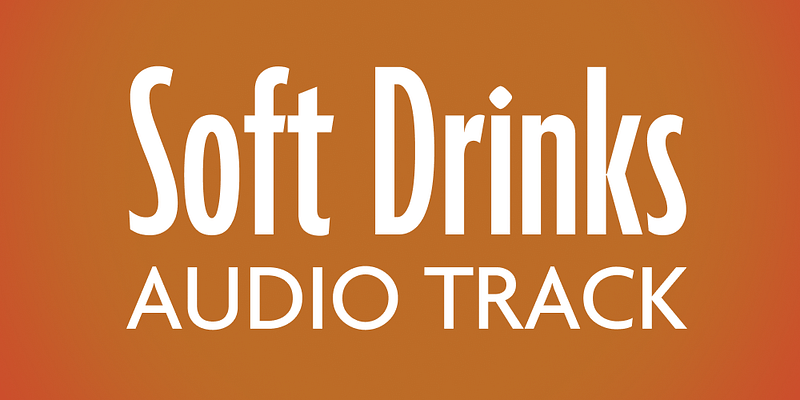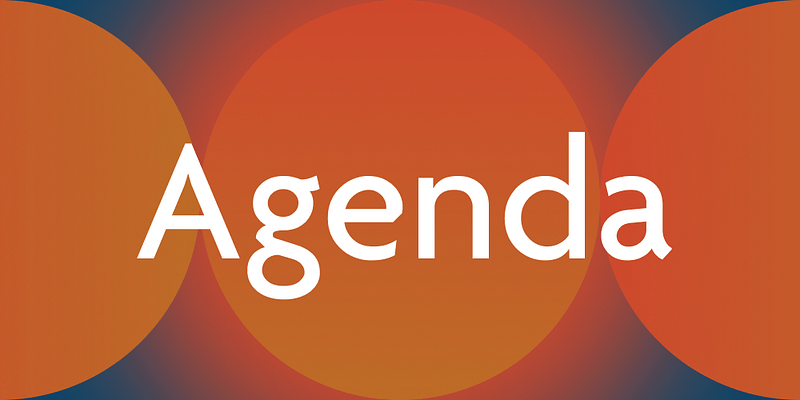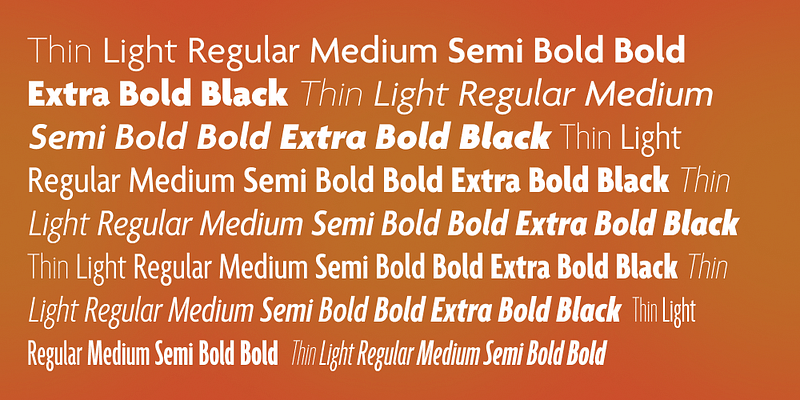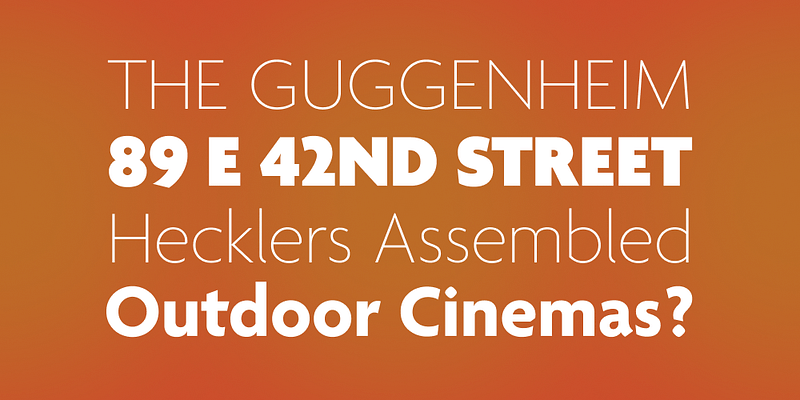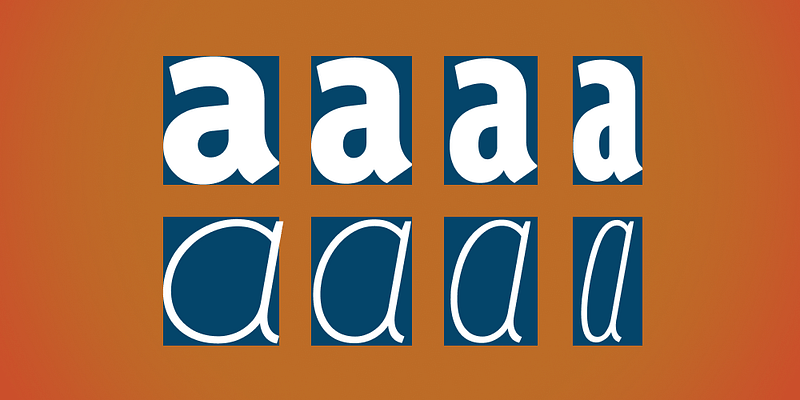
Agenda는 90년대의 상징적인 서체 중 하나입니다. 그 광범위한 패밀리는 완전히 정비되었고 Agenda One으로 재출시되었습니다. 깔끔하고 매끈한 휴머니스트 산세리프체는 Thin에서 Black까지의 Regular, Condensed, Extra Condensed 및 Compressed 폭과 무게의 타이포그래피 올인원 솔루션입니다.
Agenda One에는 현재 Agenda 소매에 설정된 문서가 Agenda One으로 변경될 때 문자 폭이 약간 다르게 리플로우될 가능성이 충분히 있습니다. 헤드라인 및 보다 큰 유형의 리플로우는 더 넓은 스타일에서 더 적게 발생하고 더 좁은 스타일에서는 가능성이 더 높지만 텍스트 크기에 대해서는 보장됩니다. 상위 악센트나 완전히 새로운 커닝과 같은 기타 디자인에 있어서의 차이로 인해 사용자는 자신의 레이아웃을 훨씬 더 만족스러운 Agenda One 세부 사항에 맞게 조정하기를 원할 것입니다.
Greg Thompson은 1980년대 후반부터 대기업, 광고 대행사를 비롯한 다양한 기업의 시각적 환경과 브랜딩 디자인 언어의 일부가 된 인기 서체를 개발해 왔습니다. 역사적 맥락과 현대적인 시각적 고려 사항이 결합된 Greg Thompson Type의 글꼴은 특정 시대를 초월하여 다양한 분위기를 표현합니다. 각 글꼴 패밀리는 영화 포스터부터 식품 포장, 서적 출판 등 디자이너의 무한한 아이디어를 더욱 돋보이게 하는 카멜레온과 같습니다.